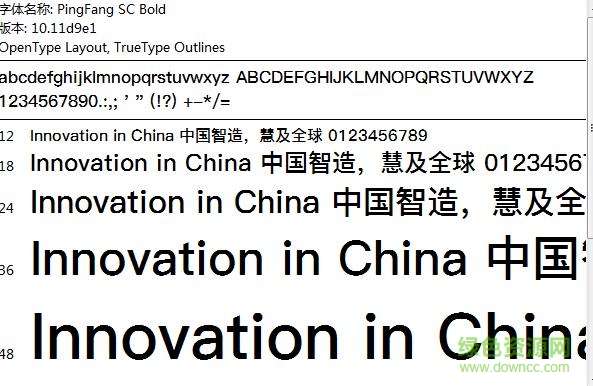
蘋(píng)方簡(jiǎn)中粗體字體
蘋(píng)方粗體字體是專(zhuān)用于蘋(píng)果設(shè)備上的一款粗體字體,看起來(lái)圓潤(rùn)和溫和,在現(xiàn)代的高分辨率顯示屏上有著出色的顯示效果,感興趣的朋友歡迎下載使用!
蘋(píng)方粗體字體簡(jiǎn)介
蘋(píng)方粗體字體是蘋(píng)果專(zhuān)門(mén)針對(duì)中國(guó)用戶(hù)推出的中文字體,它具有現(xiàn)代感的外觀和清晰易讀的屏幕顯示效果,并同時(shí)支持簡(jiǎn)體中文和繁體中文。
蘋(píng)方粗體字體